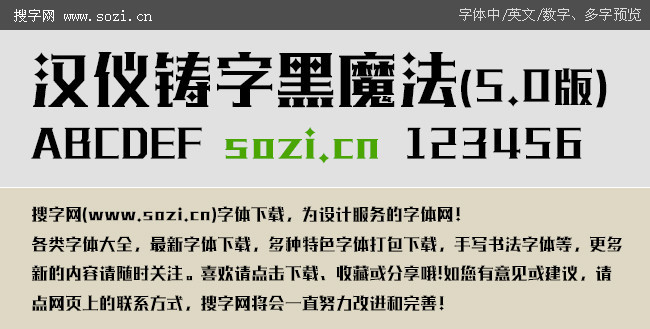
漢儀鑄字黑魔法5.0
搜字網(wǎng)提供一款漢儀鑄字黑魔法5.0中文字體下載,漢儀鑄字黑魔法這款字體有棱有角,每一個(gè)筆畫(huà)都很直,有著較強(qiáng)的力量感,也很穩(wěn)重,同時(shí),筆畫(huà)的兩端都帶有延伸,為字體增加了個(gè)性,非常的帥氣,能夠適用于藝術(shù)設(shè)計(jì)、包裝印刷、海報(bào)設(shè)計(jì)、圖形設(shè)計(jì)等領(lǐng)域。(如需要商用請(qǐng)聯(lián)系漢儀字庫(kù)購(gòu)買版權(quán))